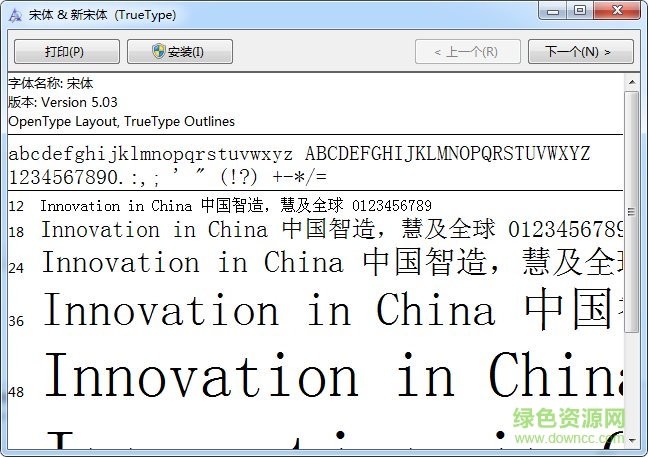
simsun字體其實(shí)就是大家經(jīng)常用到的微軟宋體。這款字體為xp系統(tǒng)原裝字體,可用于辦公、設(shè)計(jì)使用。支持中英文、阿拉伯?dāng)?shù)字輸出。有需要的用戶歡迎在綠色資源網(wǎng)下載使用。
Xp系統(tǒng)一般都自帶有這個(gè)字體,也就是我們通常所說(shuō)的宋體。也叫微軟宋體,是微軟購(gòu)買的針對(duì)中文用戶使用的字體。
宋體,是在中國(guó)宋朝發(fā)明的一種漢字印刷字體。筆畫有粗細(xì)變化,而且一般是橫細(xì)豎粗,末端有裝飾部分(即“字腳”或“襯線”),點(diǎn)、撇、捺、鉤等筆畫有尖端,屬于白體,常用于書籍、雜志、報(bào)紙印刷的正文排版。因從明朝傳入日本,而又稱為明體、明朝體。